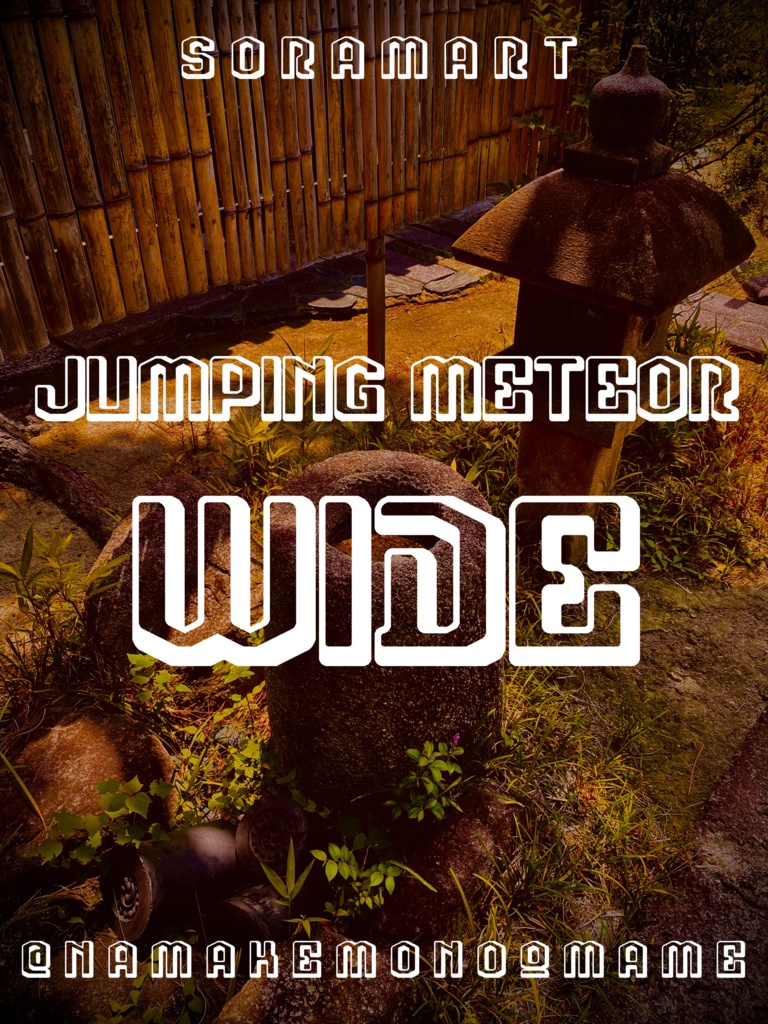
そらマートフォントデータ”Jumping Meteor Wide”Digital2,500 JPY放入購物車Buy a GiftAbout Giftゲーミングポップな白抜きフォントの太字版 "Jumping Meteor Wide" です。 「TrueTypeフォントファイル」という形式です。 ダウンロードした後、Zipファイル内のデータをインストールしてお使いください。 このフォントは商用利用可となっております。 お客様の制作・創作活動のお役に立てれば幸いです。 ※使用上の注意事項などは、添付のReadmeをお読みください。そらマートVisit FANBOX!Fontsフォントデータ”Rock Cut Serif”そらマート2,500 JPYFontsフォントデータ”Rock Cut Drop Wide”そらマート0 JPYFontsフォントデータ”Rock Cut Drop”そらマート0 JPYFontsフォントデータ”Longtail Sans Serif Slashed”そらマート2,500 JPYFontsフォントデータ”Longtail Sans Serif Bold”そらマート2,500 JPYFontsフォントデータ”Longtail Sans Serif”そらマート2,500 JPYFontsフォントデータ”Pretty Commando”そらマート2,500 JPYFontsフォントデータ”Abyss Dive Punk Retro”そらマート2,500 JPYFontsフォントデータ”Abyss Dive Punk Wide”そらマート2,500 JPYFontsフォントデータ”Abyss Dive Punk”そらマート2,500 JPYFontsフォントデータ”Emerald Sphere Sprite”そらマート2,500 JPYFontsフォントデータ”Emerald Sphere Long”そらマート2,500 JPYFontsフォントデータ”Emerald Sphere”そらマート2,500 JPYFontsフォントデータ”Monolith Glitch”そらマート2,500 JPYFontsフォントデータ”Monolith Formula”そらマート2,500 JPYFontsフォントデータ”Rolling Cute”そらマート2,500 JPYFontsフォントデータ”Tricky Wire Merge”そらマート2,500 JPYFontsフォントデータ”Tricky Layer Wide”そらマート2,500 JPYFontsフォントデータ”Tricky Layer”そらマート2,500 JPYFontsフォントデータ”Popcorn Tab Plasma”そらマート2,500 JPY查看更多